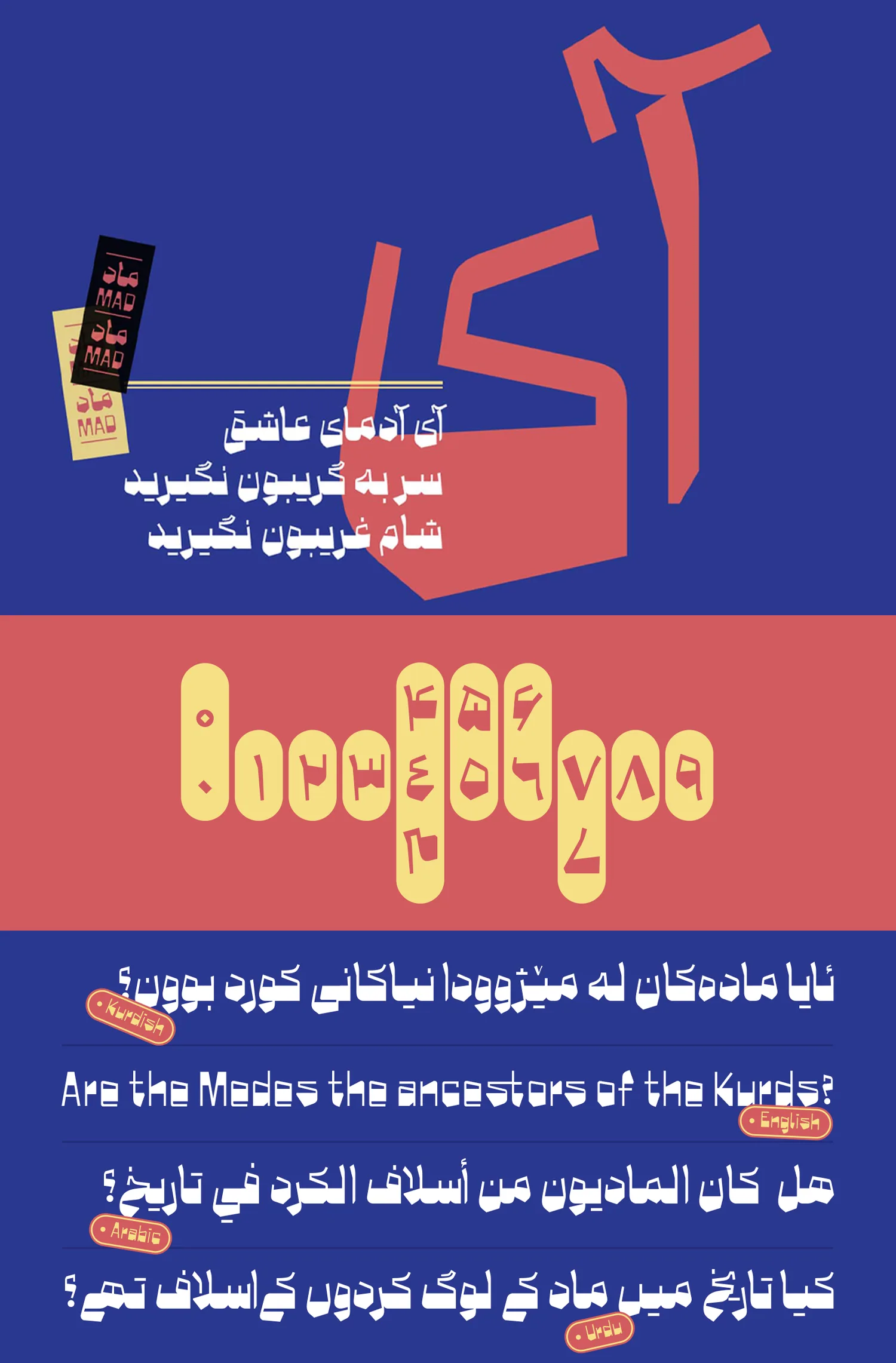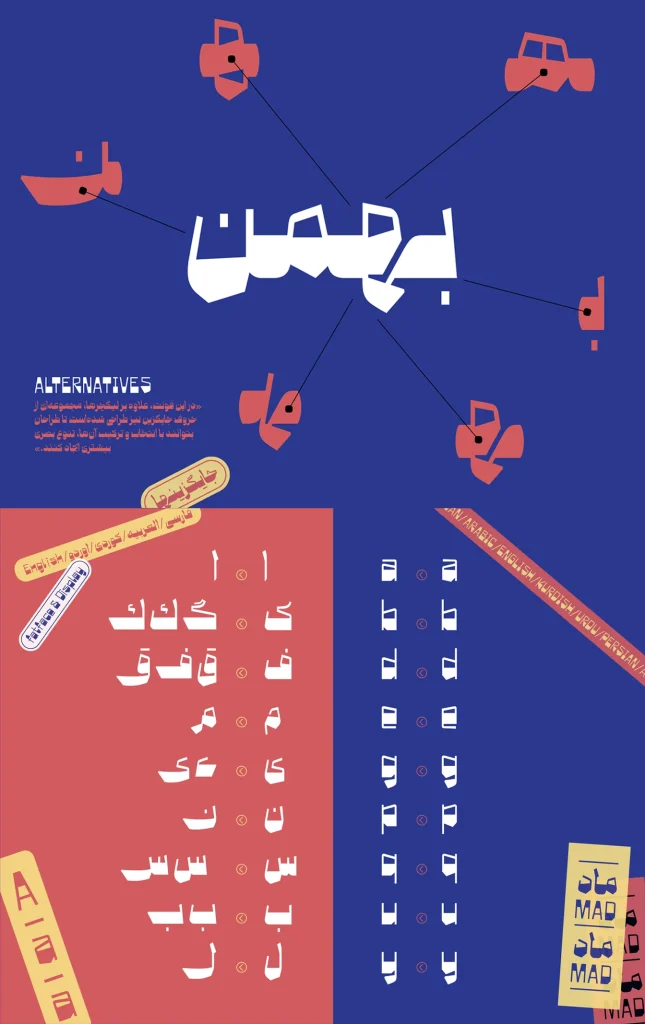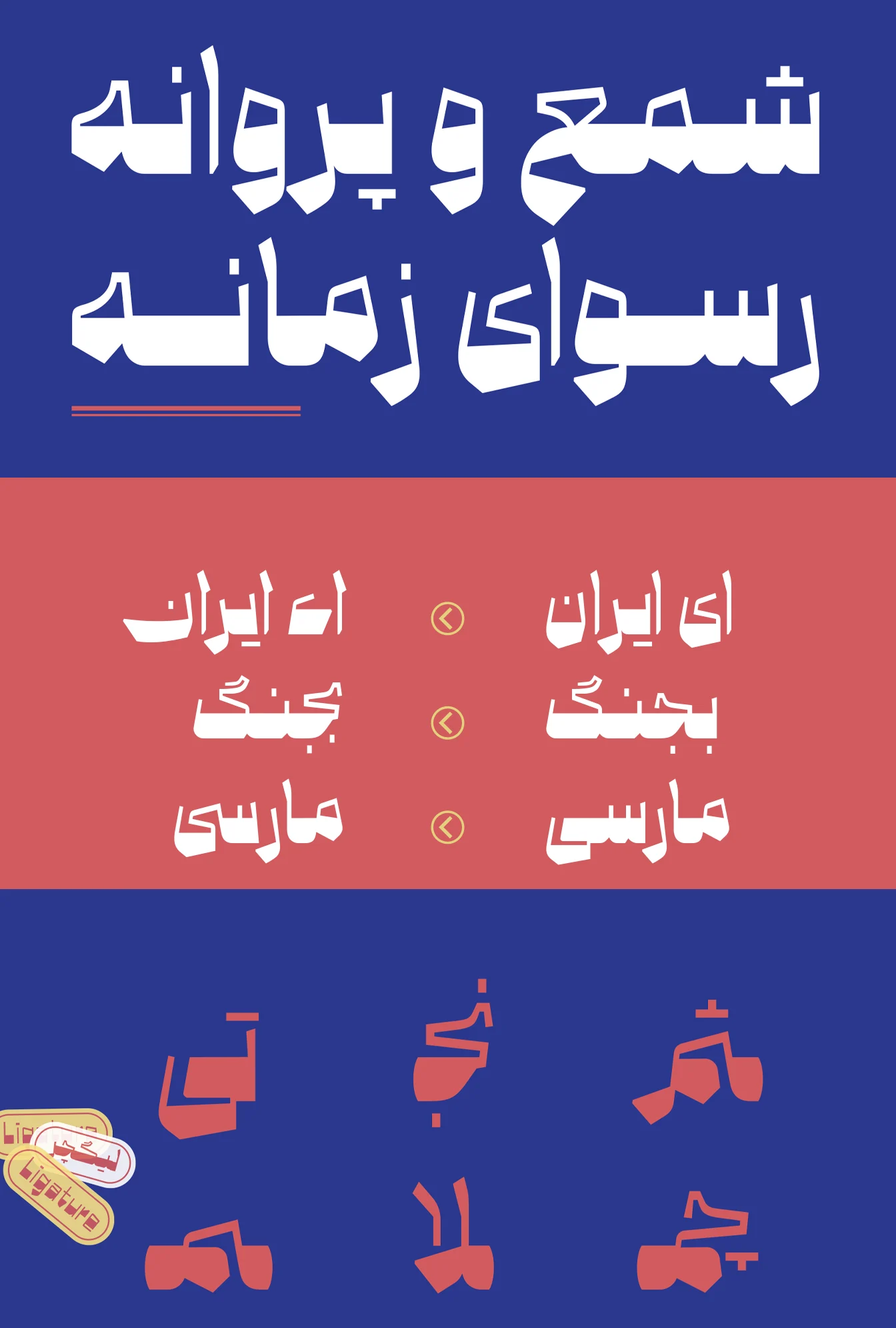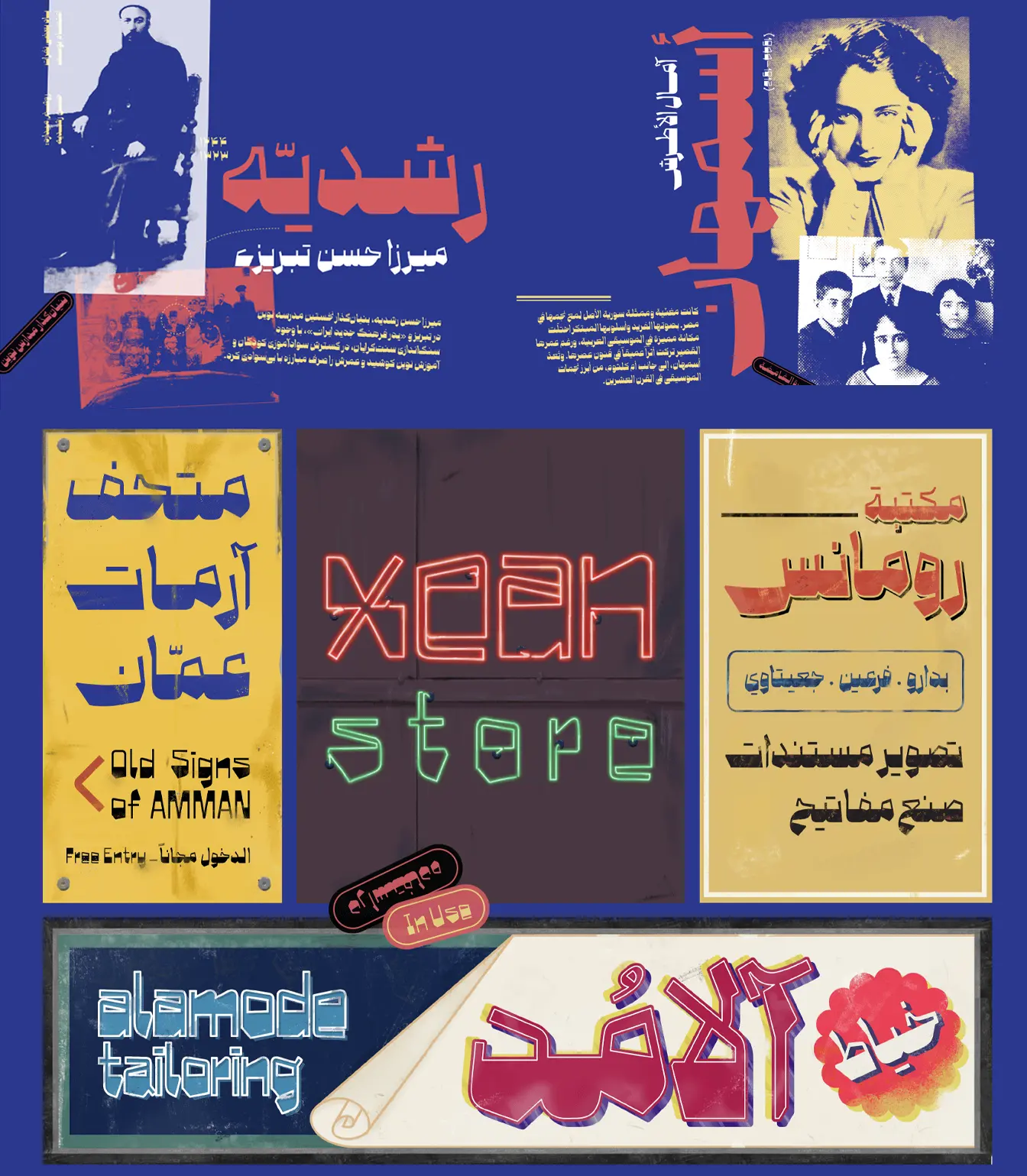
فونت ماد (Mad)
فونت ماد (به انگلیسی: Mad) یکی دیگر از سری فونتهای بر پایه خط نسخ است که کمی هم از خط ثلث در طراحی آن الهام گرفته شده است. این فونت که ظاهری جدی، قدیمی و نوستالژی و دارای چشمیها و خط کرسی بزرگ است، برای استفاده در عناوین، متون کوتاه، طراحی پوستر و تبلیغات کاربرد دارد. فونت ماد رایگان نیست و در یک نسخه وزنی Bold ارائه شده است.
حسامالدین باقریان در طراحی این فونت خط ثلث را بهعنوان الگوی خود قرار داد و با ایجاد ساختاری هندسی که از دفرماسیون بدن سوسک ها الهام گرفته است، حروف را بهشکلی دفرمه کرده که ظاهری خوانا و نمایشی بگیرند. توسعه این قلم نیز توسط شهرزاد اکبری انجام گرفته که با مراجعه به صفحه پروفایل وی میتوانید دیگر آثار توسعه داده شده وی که با همکاری سایر طراحان خلق شده را مشاهده کنید.
در ادامه شما را بیشتر با این فونت آشنا کرده و با بررسی سبک طراحی و مشخصاتی که این قلم دارد کاربردهای متنوع آن را با هم مرور خواهیم کرد.
فونت فارسی ماد ظاهری قدیمی و نوستالژی دارد که بر پایه نسخ و هندسه طراحی شده است. این فونت یادآور تابلوها و سردر مغازهها در دورههای قدیمی عموما دهه ۵۰ تا ۷۰ است که پیش از این قلمهایی با همین سبک همچون فونت صداقت را معرفی کردهایم.
در این گونه فونتها تمرکز روی سبک طراحی که ظاهر فونت را نمایشی کرده و نگاه مخاطب را به خود جلب کند اهمیت دارد. از همینرو با فونتی مواجه هستیم که در خط کرسی دارای ضخامت بسیار بالا اما در خطوط عمودی دارای ساختاری بسار نازک و شکننده است.
برای افزایش خوانایی فونت در ابعاد گوناگون، بهویژه در کاربردهای چاپ محیطی چشمی حروف بر خلاف دیگر قلمها بزرگتر است که همین امر فونت را بیشتر نمایشی میکند. برای رسیدن به نقطه عطف نمایشی بودن قلم نیز، از حروف و ترکیبات جایگزین استفاده شده است که در ادامه بیشتر با آنها آشنا خواهیم شد.
فونت چند زبانه ماد با اعداد استاندارد
فونت ماد محدود به زبان فارسی نیست و از دیگر زبانهای خاورمیانهای مثل کردی، عربی و اردو نیز پشتیبانی میکند. در هر زبان اعداد حالت استاندارد خود را حفظ کرده و همچنین کاراکترهای خاص و اعراب هر زبان نیز بر اساس استاندارد همان زبان تایپ میشود.
فونت انگلیسی دیگر زبان پشتیبانی شده در این فونت است که همان سبک طراحی نسخه فارسی را در خود دارد. طوری که حروف در خط کرسی و انتهایی دارای ضخامت بالا اما در مقابل در خطوط عمودی دارای ظاهری نازک هستند. چشمیها نیز مطابق با نسخه فارسی، اندازه بزرگی دارند.
از دیگر نقاط قوت فونت در بخش زبان میتوان به وجود نسخههای مخصوص اعداد فارسی هک شده و نسخه بدون حروف انگلیسی اشاره کرد. در نسخه اول هیچ عدد انگلیسی یا عربی وجود ندارد که باعث میشود حتی زمانی که صفحه کلید شما انگلیسی یا عربی باشد، اعداد به شکب فارسی تایپ شوند.
در نسخه دوم نیز که بدون حروف و اعداد انگلیسی است، صرفا گلیفهای فارسی قرار دارند. این نسخه برای توسعه نرمافزاری مناسب است تا اگر خواستید برای زبان انگلیسی از فونت دیگری استفاده کنید.
فونت ماد با حروف جایگزین
تنوع در حروف جایگزین یکی از نقاط قوت این فونت نمایشی است. در فونت ماد میتوانید برخی از حروف و ترکیبات را با چند ظاهر مختلف تایپ کنید که آزادی عمل بیشتری برای نوشتار کلمات به شما میدهد. این تفاوت در نوشتار ساختار فونت را زیباتر کرده و از انجام کارهای گرافیکی و زمانبر با برنامههای تخصصی مثل ایلاستریتور جلوگیری میکند.
ترکیبات و حروفی مثل «ی، ن، ـج، ـی، ـیم، ـم، ـک، ـمـ، ف، ق، ل، س، ش، ب، ـهـ» در این فونت دارای تایپ جایگزین هستند که بر اساس فایل راهنمای فونت میتوانید آنها را تایپ کنید. این ترکیبات باعث دیده شدن برخی کلمات و تمرکز روی آنها میشوند که در کاربردهای تبلیغاتی به جذب بیشتر نگاه مخاطب کمک میکند.
کاربردهای فونت ماد
فونت ماد دارای ظاهری شارپ، جدی و نمایشی است که همین امر موجب میشود کاربردهای مختلفی برای متون کوتاه و عناوین داشته باشد. ترکیب ظاهر هندسی، خط نسخ و کمی هم ادغام ثلث در این فونت سبب شده تا برای کاربردهای قدیمی و نوستالژی نیز گزینه مناسبی باشد.
کنتراست بالا در چشمی حروف، به افزایش هرچه بیشتر خوانایی این فونت کمک میکند. ادغام آن با خط کرسی ضخیم نیز باعث میشود تا بیش از پیش برای عناوین و متون کوتاه مناسب باشد، از این رو کاربردهای زیر را دارد:
- طراحی پوستر، جلد مجلات و جلد کتاب با موضوعات تاریخی، فرهنگی، نمایشی و هنری.
- طراحی تابلو سردر مغازهها به ویژه با موضوعات نوستالژی و قدیمی.
- استفاده در تامنیل و کاور پست شبکههای اجتماعی.
- استفاده در حوزه تبلیغات و بستهبندی محصولات.
- طراحی کارهای گرافیکی و خلاقانه.
در تصاویر بالا نیز برخی از ویژگیهای این فونت را با توجه به کاربردهای ذکر شده مشاهده میکنید. مسلما فونت ماد محدود به این موارد نبوده و با توجه به قوه تخیل و ایدههایی که در ذهنتان دارید، میتوانید استفادههای گوناگون از این قلم داشته باشید.